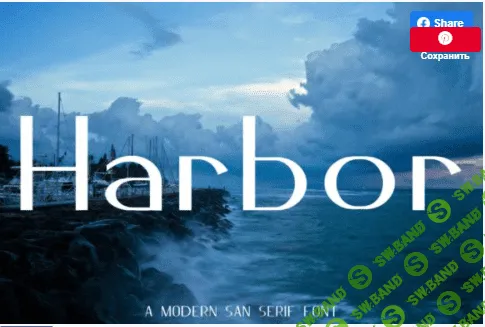
Название: Harbor Font (2021)
Harbour - это простой и аккуратный шрифт без засечек. Его можно легко сопоставить с невероятно большим набором проектов, поэтому добавьте его к своим творческим идеям и обратите внимание, как они выделяются среди них!